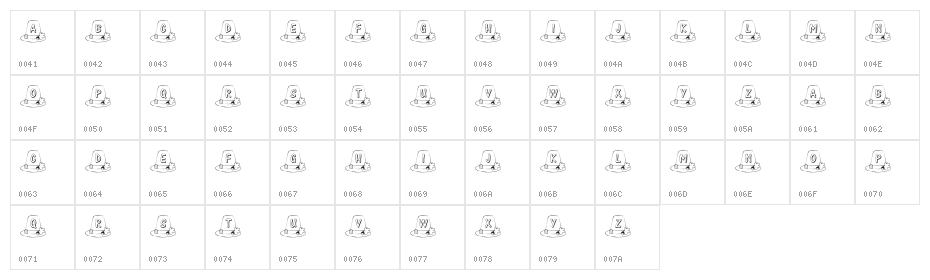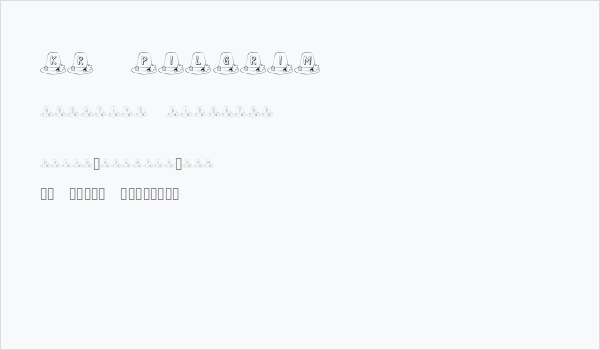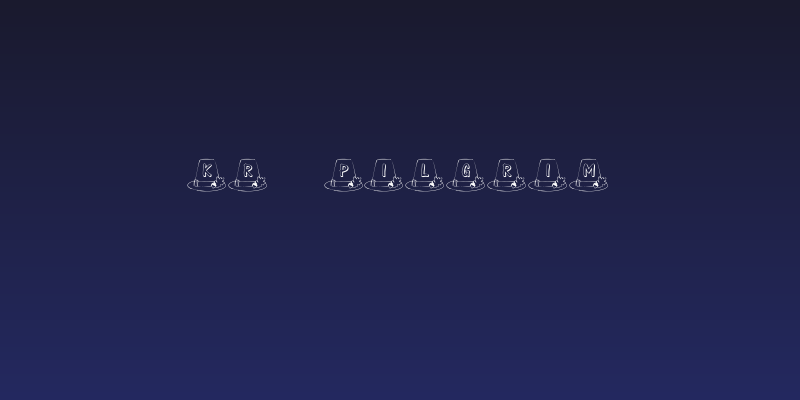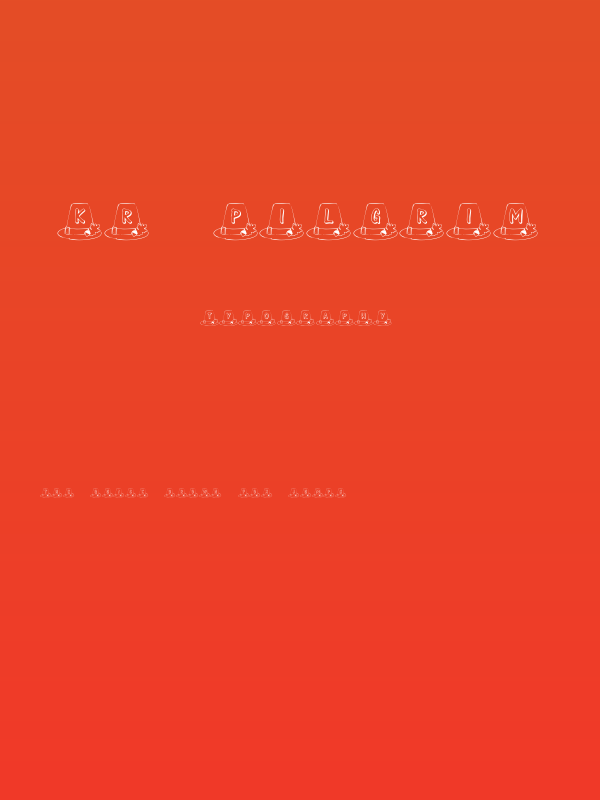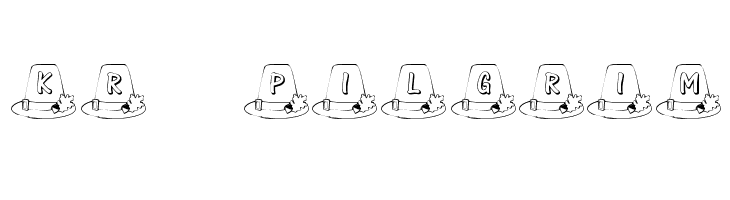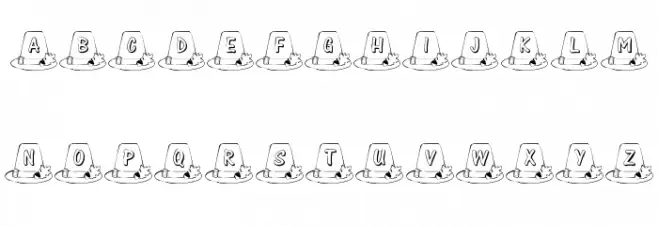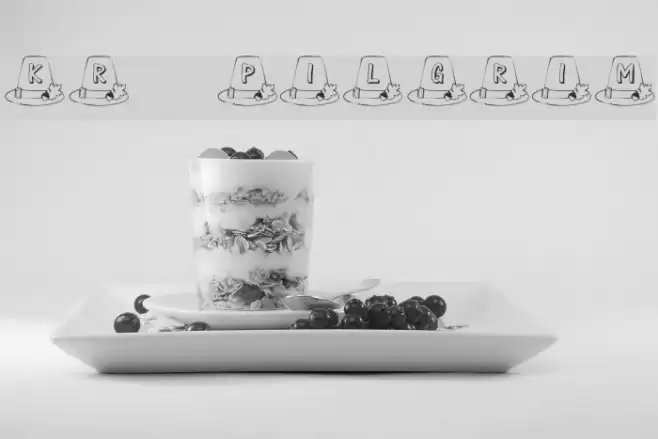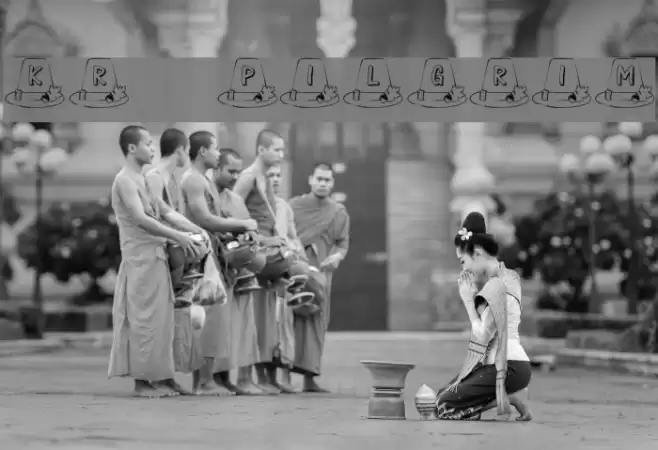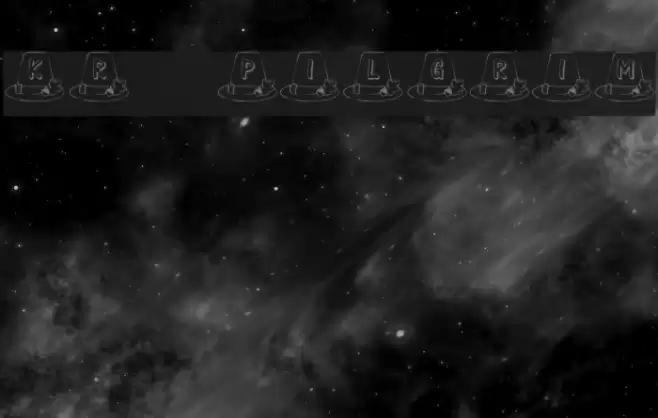
KR Pilgrim Font
| Caso de uso | Headlines, Logos, Thematic decorations |
| Projetos propostos | Ideal for Thanksgiving-themed invitations, holiday cards, seasonal posters, and festive banners. |